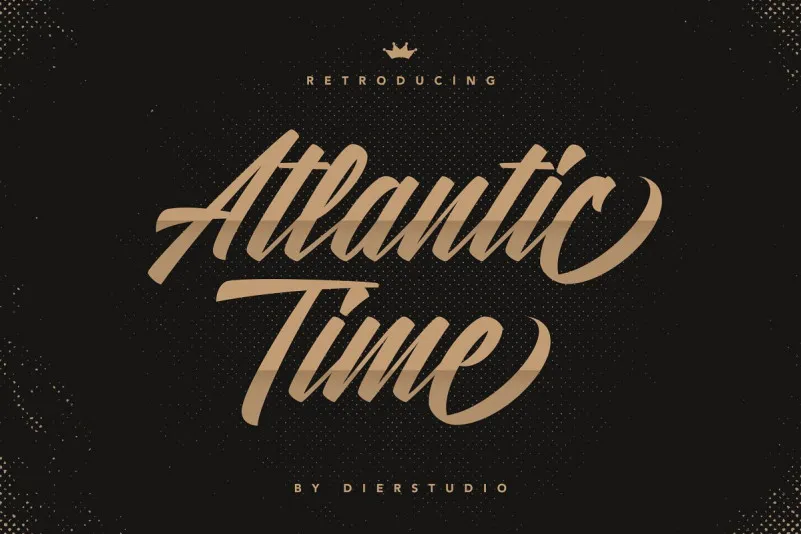
Atlantic Time Script Font
A Nova Font Script ‘Atlantic Time’ é uma criação do designer 24Design que traz uma mistura única de elegância e nostalgia para os seus projetos digitais. Esta fonte tem seis estilos diferentes, cada um com seu próprio toque vintage distintivo, garantindo que sua identidade visual seja sempre impecável e singular. Introduzida pela Atlantic Time, esta font script não é apenas uma escolha de estilo casual; ela traz à tona o charme retro dos anos 30 e 40 em cada letra, tornando-a ideal para aplicativos em variados formatos – desde pequenos logotipos até grandes outdoors. Seja você um designer gráfico ou editor de fotos que busca incorporar um toque nostálgico aos seus trabalhos, esta font se encaixa perfeitamente. O uso desta font pode dar vida à sua marca digital com um toque cuidadosamente pensado e elegante, tornando-a única na multidão. A Atlantic Time não apenas revoluciona a maneira como você visualiza o texto em seu trabalho – ela também reflete os seus esforços, dando ao design uma personalidade própria que se destaca de qualquer outro.